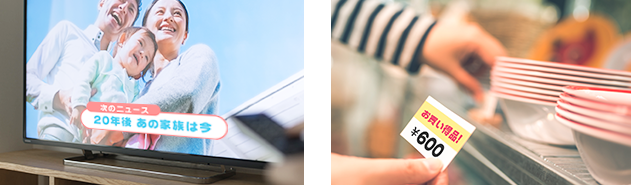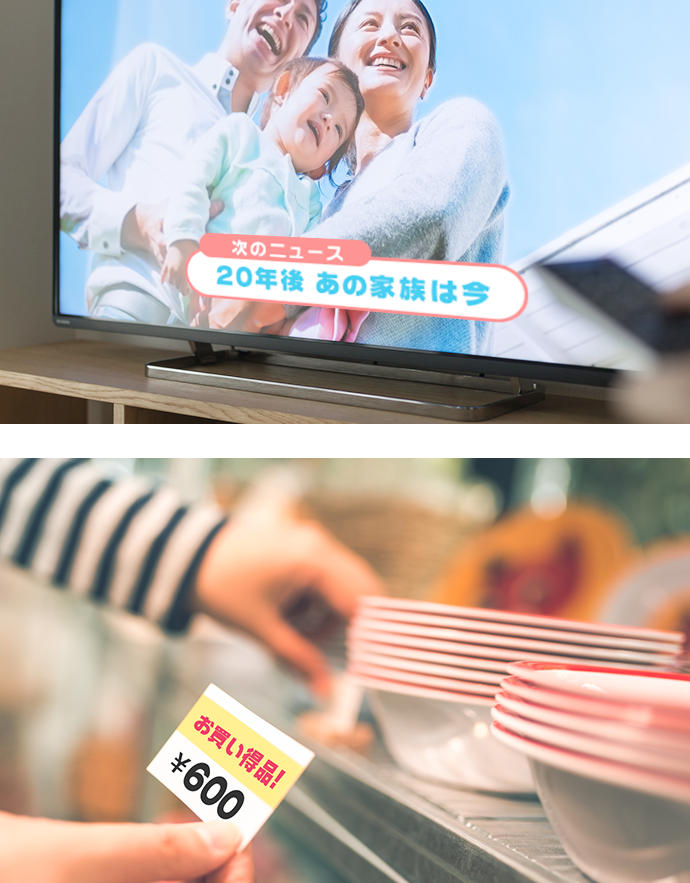
ウインクスL+JTCウインSシリーズ
「横組みに適した“かな“」をコンセプトにした”横組み専用”のフォルムです。漢字とかなの横のラインが美しくそろうため、番組テロップや店頭POPの表示などに最適。太さ (ウエイト)のバリエーション(ファミリーフォント)は4種類ご用意しています。
日本語フォントは、漢字が大きく、かな文字が小さいため、横方向のラインが美しくそろわないことが課題のひとつでもありました。それを解決したのが「ウインクスL+JTCウインS」 です。書体を“横組み専用”としたことで、横ラインを美しいフラットデザインで構成。平仮名、片仮名の形状も特徴的で、丸みのある緩やかな曲線とシルエットが魅力。美しさと実用性を兼ね備えたこだわりのフォントです。
ワープロや、パソコン、さらにはスマートフォンなどの普及により、日本でも「横書き」が習慣化してきました。そこで、“横組みに適した「かな」をつくりたい”という想いから生まれたのが「ウインクスL+JTCウインS」です。変わりゆく時代のニーズにも、NIS Fontなら素早く対応可能です。
“横組み専用”フォルムのため、番組テロップや店頭POPなどに最適です。
1970年に「じゅん」を発表。以後書体デザインに専念する。ミヤケアロー、ひげ文字等々、その書体デザイン数は30書体を越え、文字数にして36万文字に達しており、文字どおり日本の書体デザインの第一人者。 コーポレートアイデンティティ(ロゴ、制定書体)として三菱自動車、味の素ゼネラルフーズ、コニカ等を制作。タイポグラフィカルアートとして版画、レリーフ等の分野でも活躍中。